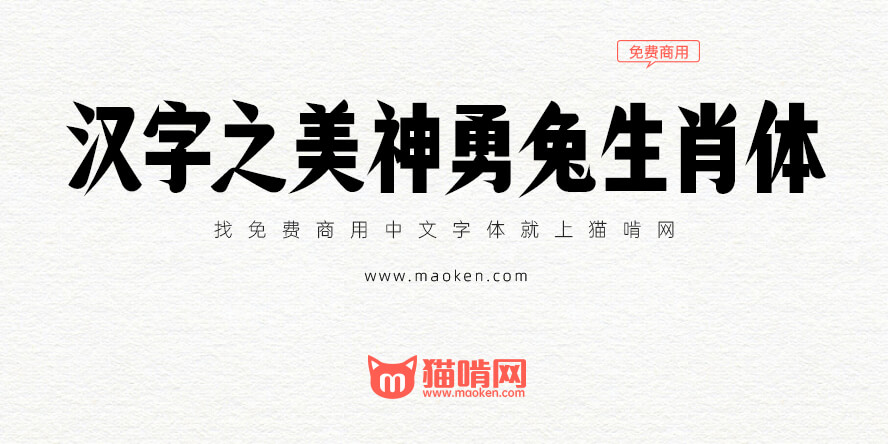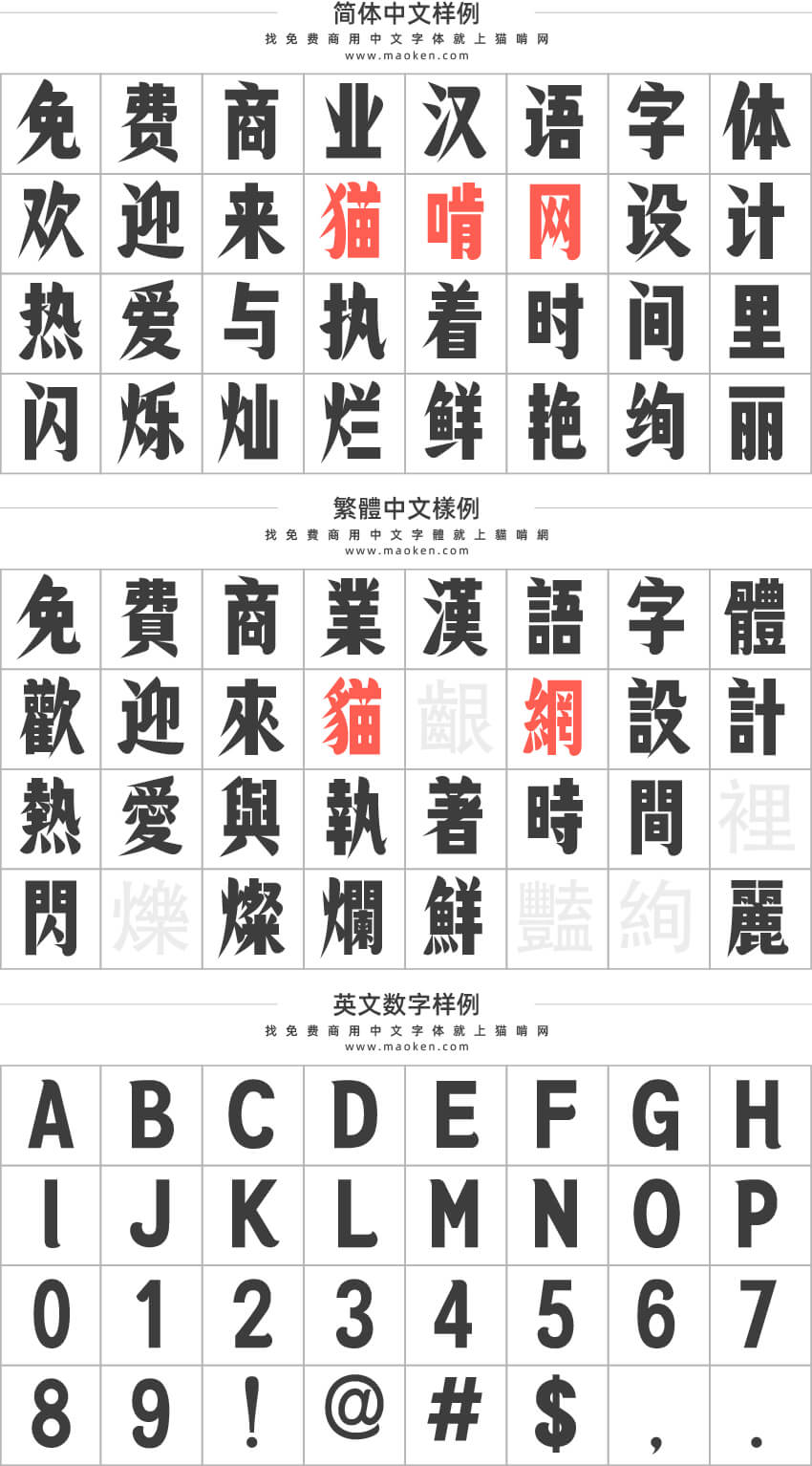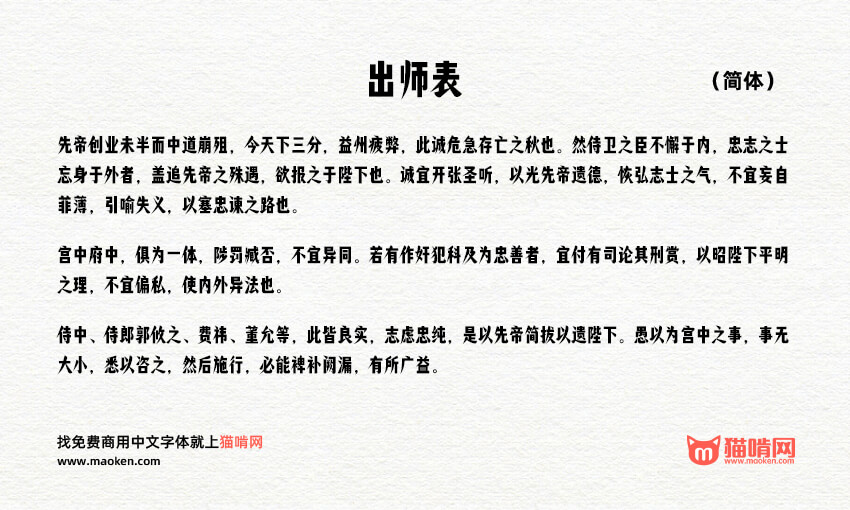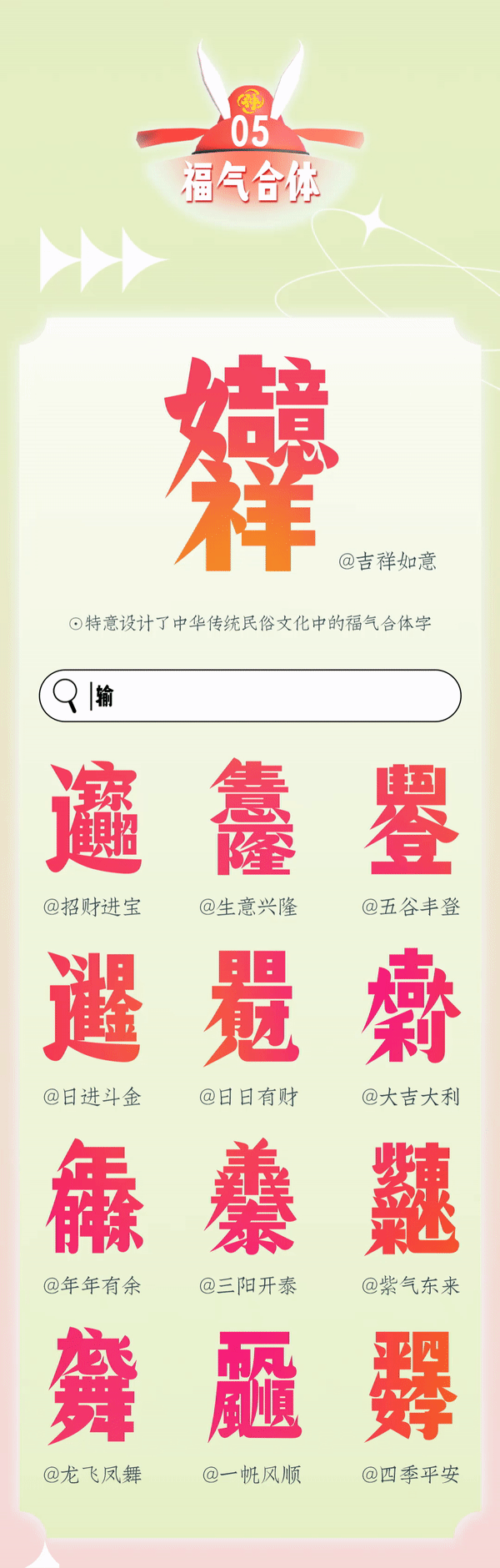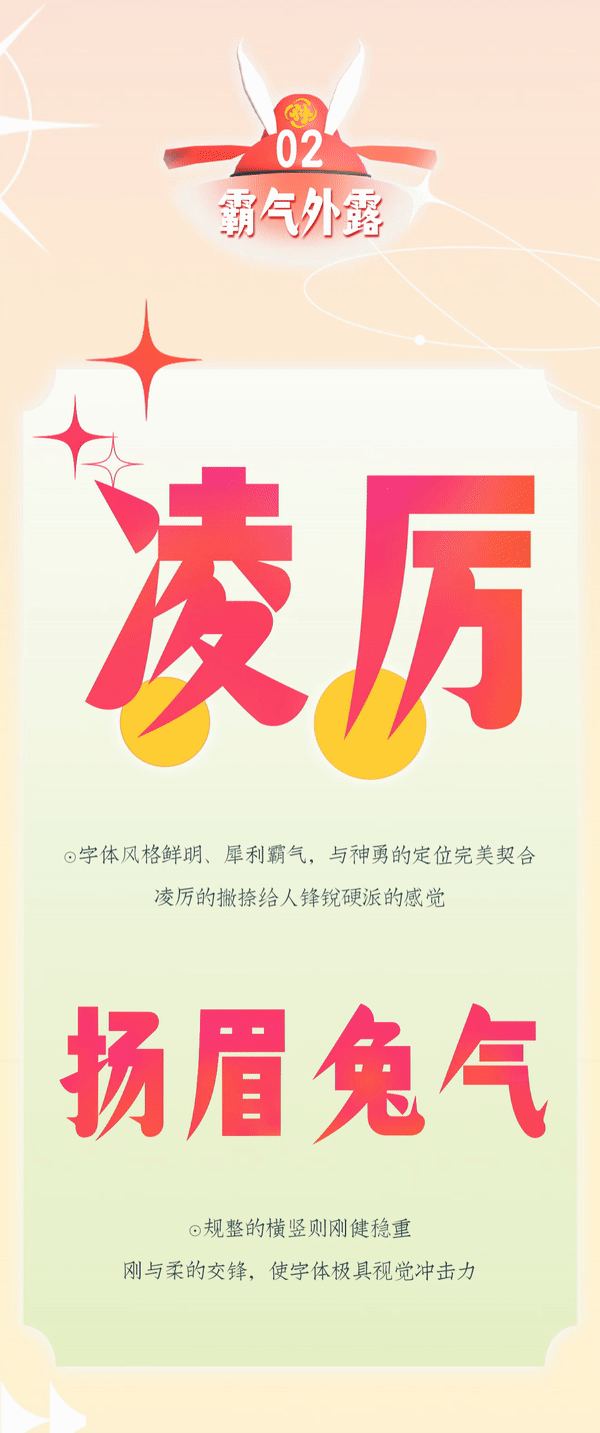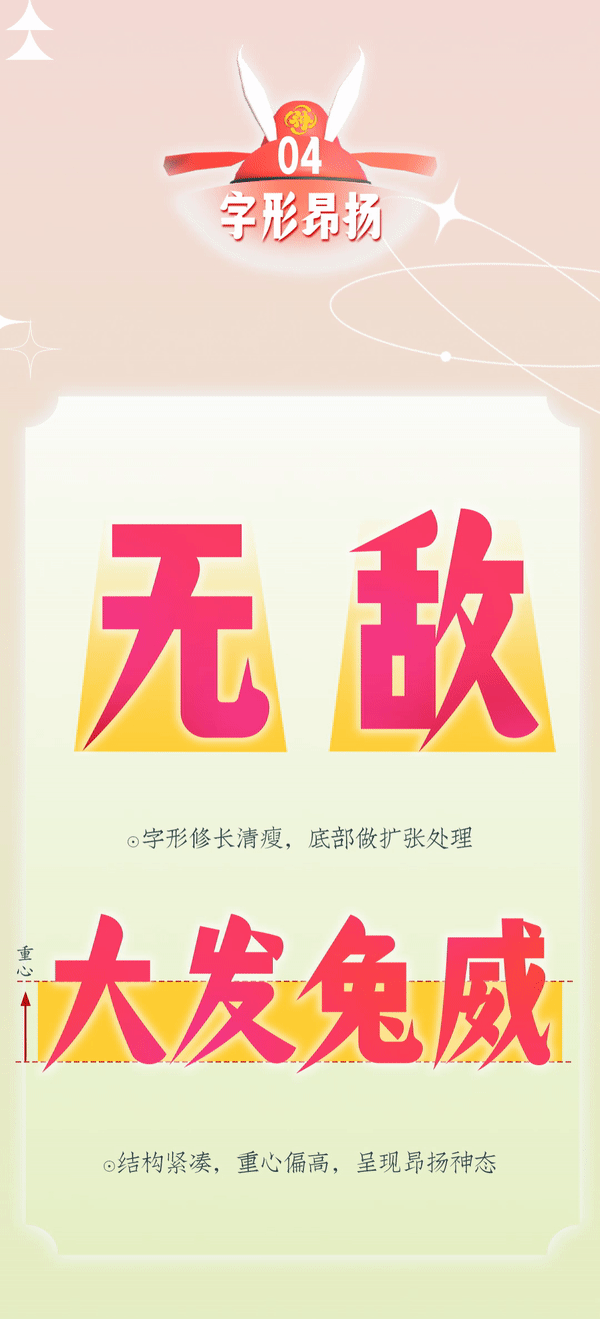
汉字之美神勇兔生肖体:融合宋、黑风格进行笔画创新的生肖字体
在虚实共生的汉字元宇宙,
字神国风元书院获得了一枚通往过去的时空密钥。
特派遣生肖守护官——神勇兔,
采撷散落在各个时空的兔年生肖印迹,
推出汉字元宇宙首款生肖字体,
汉字之美神勇兔生肖体,
深眠的宝物,将从此复活。
汉字之美神勇兔生肖体
融合宋体、黑体元素进行笔画创新的
首款兔年生肖字体。
字体风格鲜明、犀利霸气,修长清俊的字形,
凌厉的撇画,以及像兔子耳朵的笔画设计;
颠覆传统,以跨时代的创新融合,探索字形的无穷变化。
汉字之美神勇兔生肖体
风格气质:国风、刻本、个性